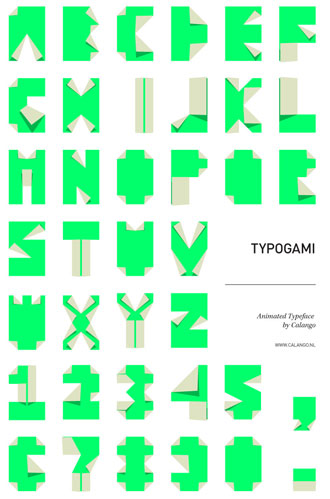
Typogami, una curiosa tipografía «animada» del estudio holandés Calango, similar a la tipografía de origami de Gesa Hansen que encontramos el año pasado.
En Typogami cada letra es un papel plegado, aunque curiosamente en vez de partir de un cuadrado como en los origamis japoneses pata negra aquí emplean una «hoja» de proporciones A4.
Unos pocos pliegues en los lugares correctos y ¡tachán! surge cada letra del alfabeto como por arte de magia.